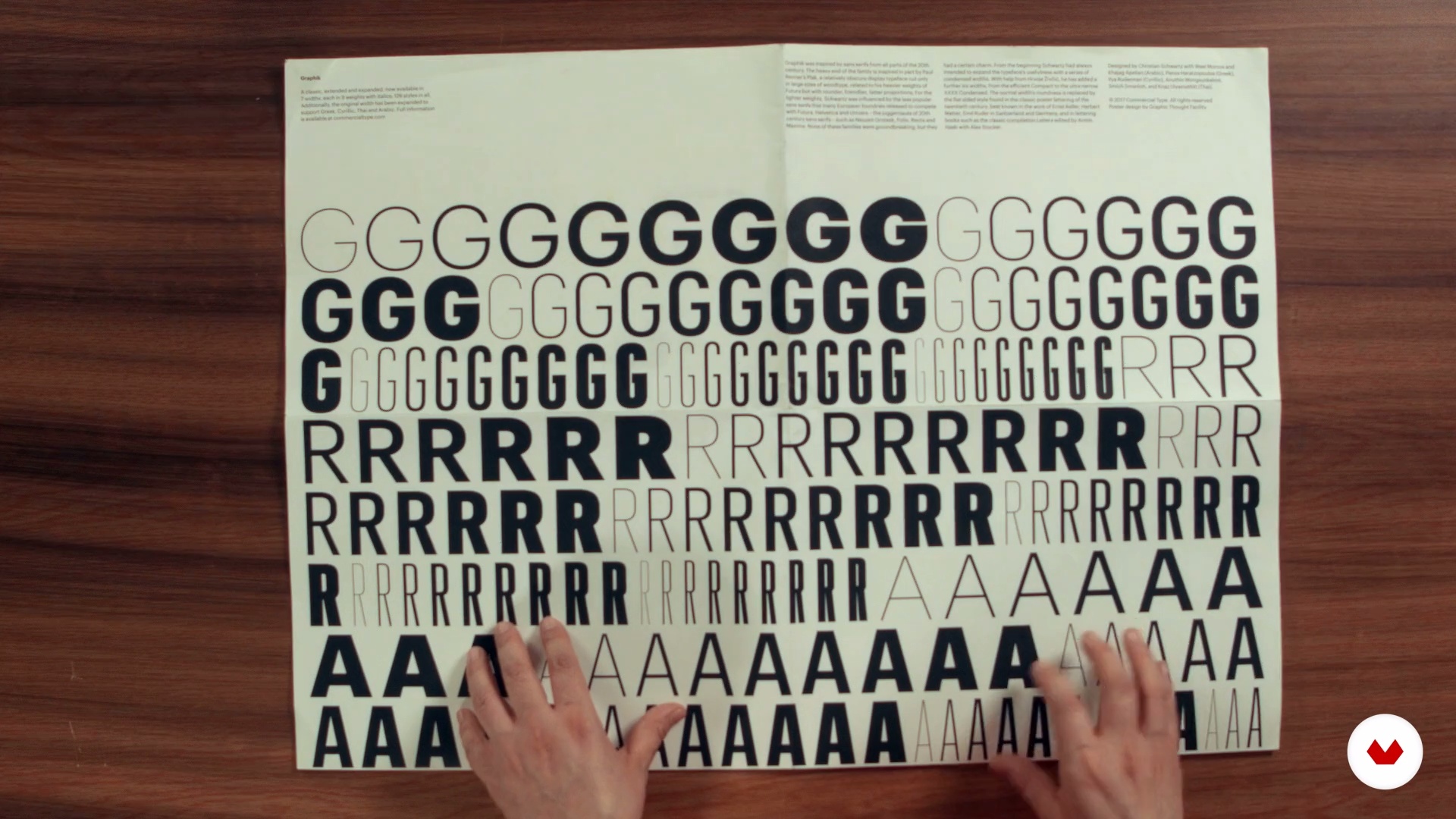
“Nous vous montrerons ici des exemples d'utilisation correcte des attributs typographiques dans un projet spécifique, en tenant compte de sa nature. ”
“Une fois que nous avons vu les attributs formels et expressifs de la typographie. nous sommes prêts à commencer la sélection typographique de notre projet. Pour réaliser les projets. nous nous basons sur des spécimens. J'en ai un ici que je vais vous montrer. que j'aime bien car il montre la disposition de la police dans toutes ses dimensions. que ce soit en de poids. de dimension. d'épaisseur. amplitude. entre autres aspects. Comme vous pouvez le voir. nous observons la source graphique. un ensemble complet de caractères ainsi que les modifications dans leur expression en fonction de l'épa...”